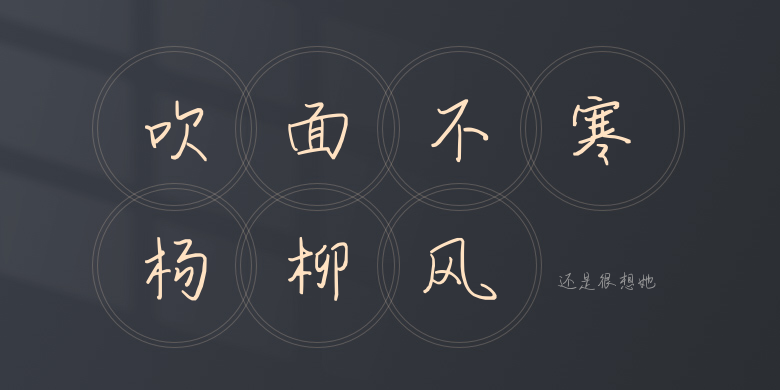
还是很想她
还是很想她,这款字体结构工整、笔画清晰,兼顾美观与易读性,适用于标题、正文、海报、包装、LOGO 等多种场景。字形优雅稳定,风格百搭耐看,适配日常排版与创意设计,让文字呈现更舒适、更具质感。还是很想她一笔一画,皆是细节,以均衡的比例、流畅的线条打造舒适视觉体验,字形端正大气,风格简约现代。无论是商业设计、品牌宣传还是日常排版,都能轻松驾驭,让文字更有格调与力量。还是很想她字体下载。